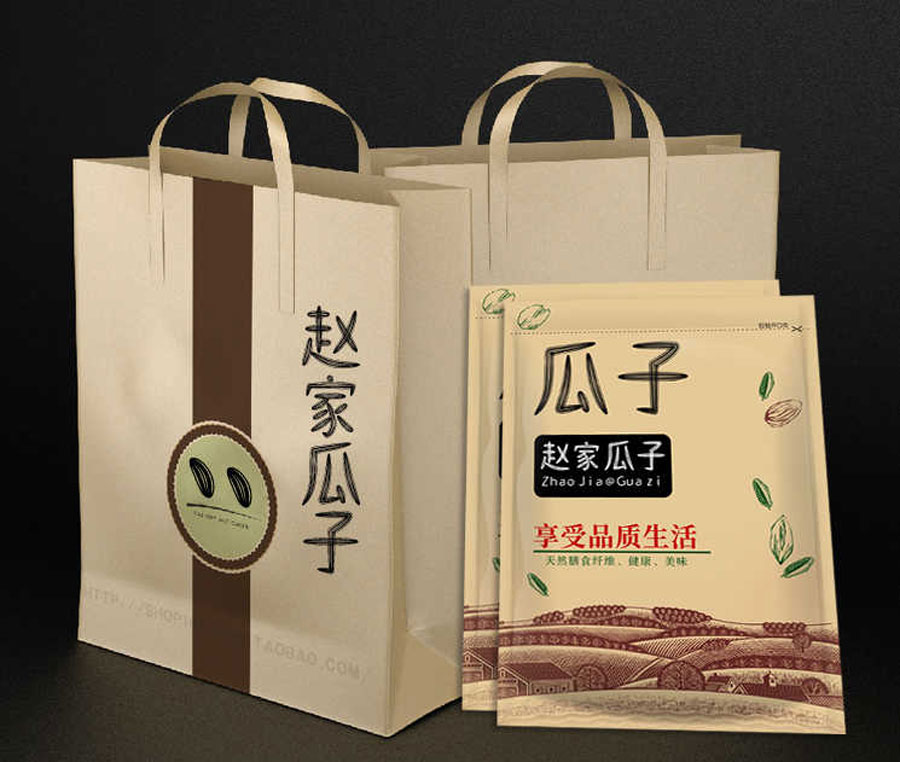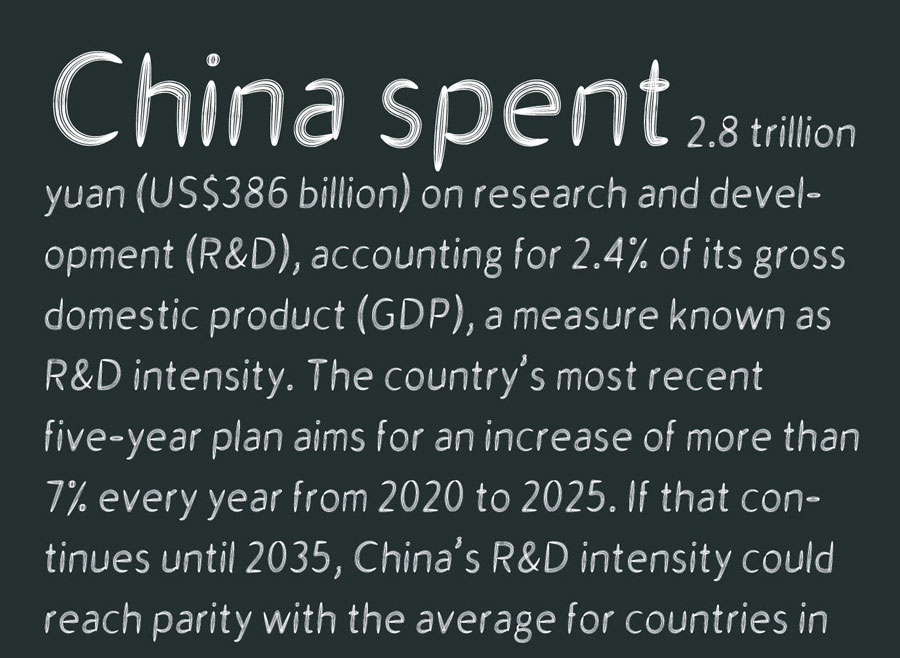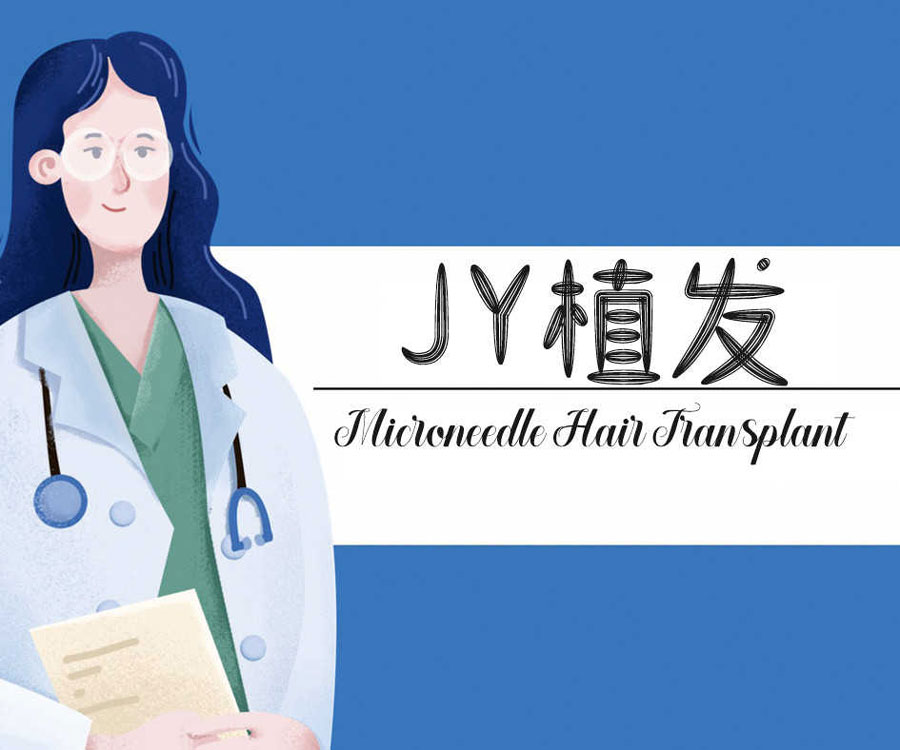
山字瓜子体是由中国大陆设计师frankleng创作的免费商用中文字体,其笔画形似瓜子,具有鲜明的可爱卡通风格,适合大字号设计场景(如海报标题、广告主视觉),但不适合小字号排版(如正文四号字以下)。
山字瓜子体是一款免费可商用的手写中文字体,是设计师 frankleng 在经营图文店期间独立开发的,由于其笔画形似瓜子,所以得名山字瓜子体。
山字瓜子体的每个字笔画末端都呈短圆弧状,模仿瓜子轮廓,整体圆润饱满、活泼俏皮。适合需要传递轻松、童趣氛围的场景,如儿童产品、社交媒体配图、卡通动画字幕等。但因在小字号(如四号字以下)时易显模糊,并不适用于正文排版,所以更推荐标题、标语等短文本的大字号应用。
山字瓜子体包含 GB2312 规范的 6763 个常用中文字以及若干英文常用字母和标点符号,首发于 bilibili 并明确支持免费商用。唯一的缺点就是因笔画复杂度高,体积明显咬大于常规字体,如果预览失败可以直接去字体来源中查看原视频。